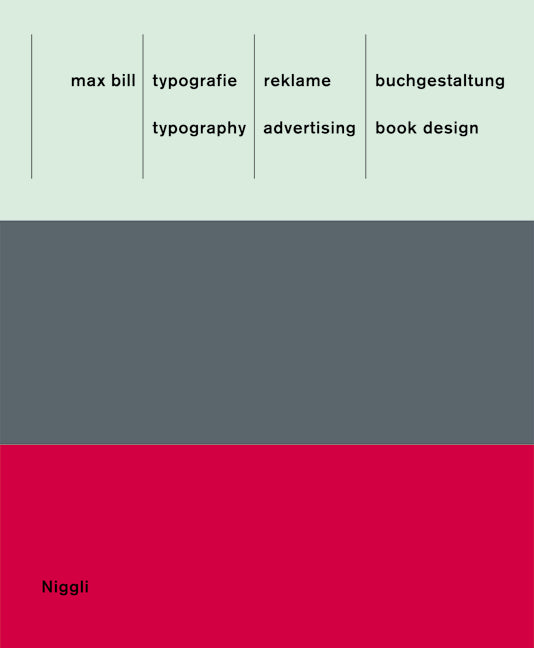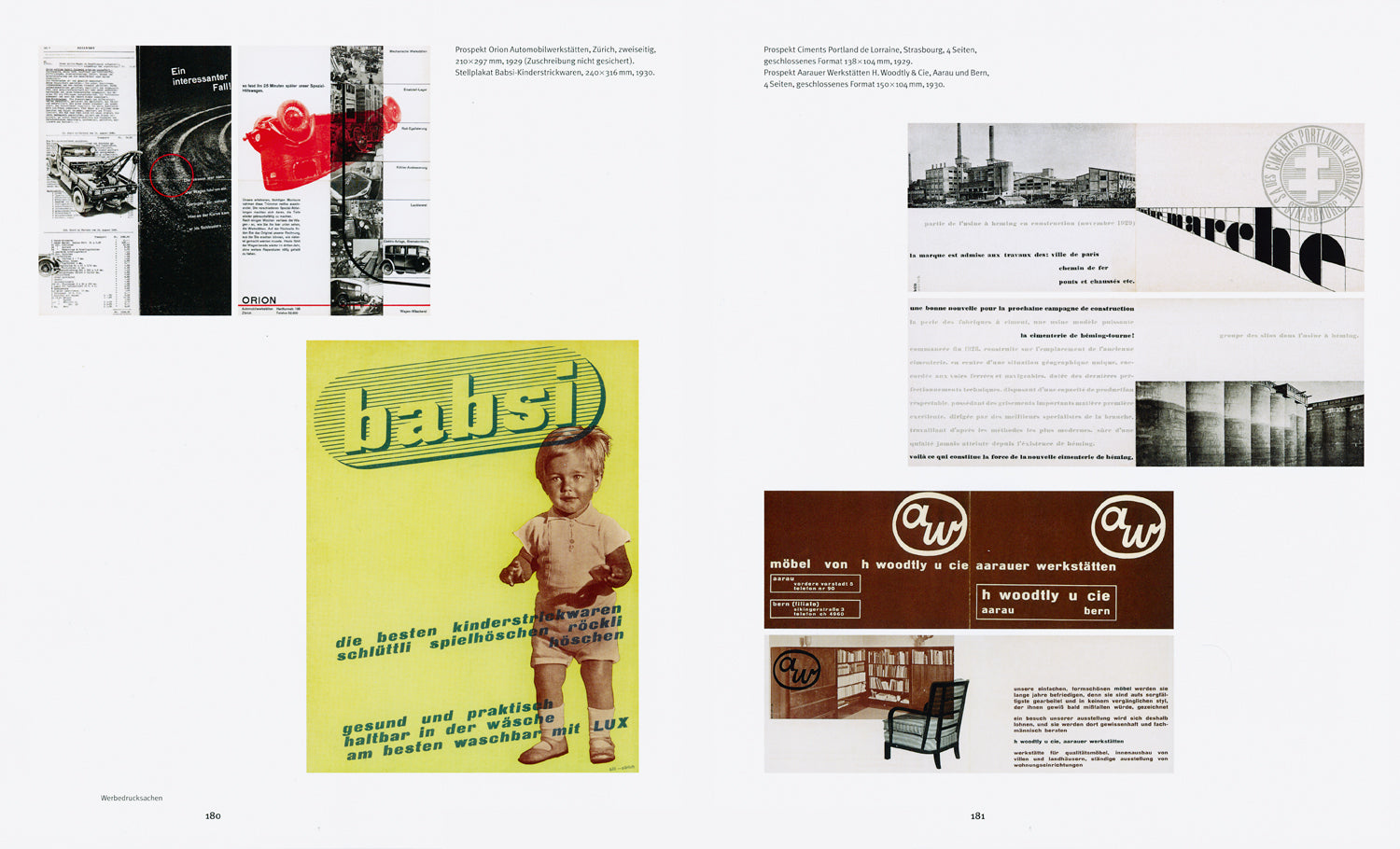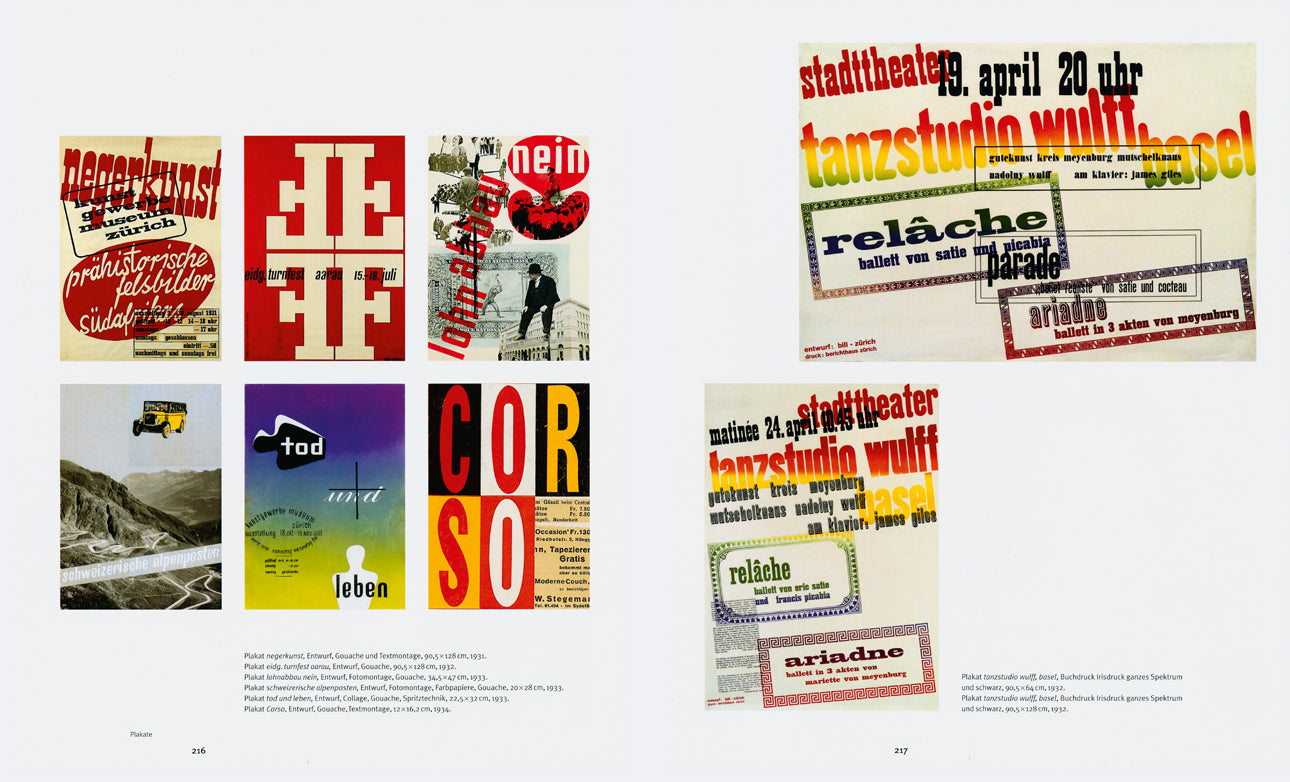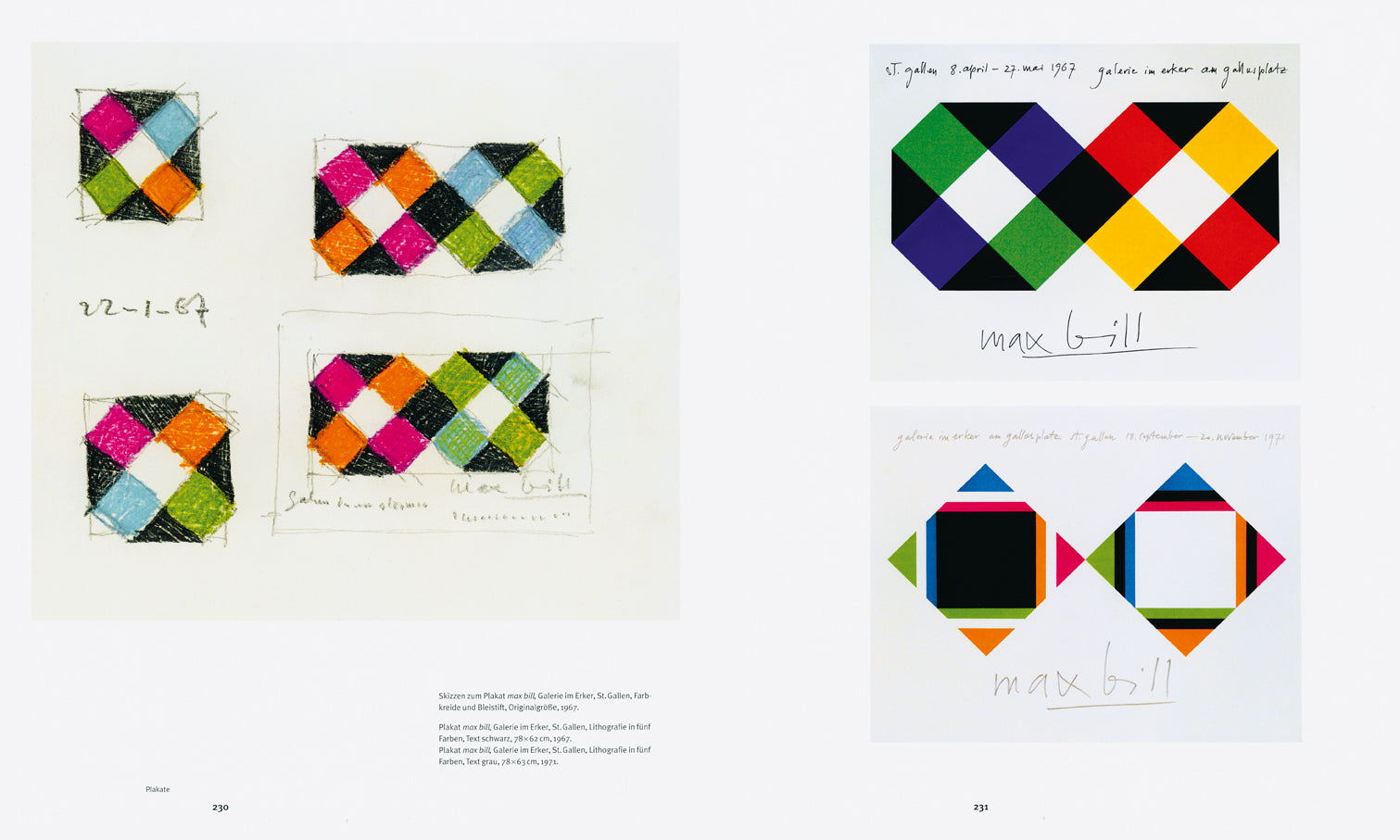
Max Bill: Typografie. Reklame. Buchgestaltung
Das vorliegende Buch gibt einen umfassenden Einblick in ein Gebiet aus dem Schaffen Max Bills, dem bisher wenig Aufmerksamkeit entgegengebracht wurde: seinen typografischen Arbeiten, Reklame- und Buchgestaltungen. Obwohl sich Max Bill zeitlebens am liebsten als Architekt sah, stammen gerade seine ersten Arbeiten mehrheitlich aus dem Gebiet der Gebrauchsgrafik und stellen einen wesentlichen Teil seines künstlerischen Œuvres dar. Die Publikation verdeutlicht, dass fast alles, was die schweizerische Avantgarde um 1930 an Lebens- und Wohnreform durchführte, im Atelier «bill-zürich reklame» für die Öffentlichkeit visualisiert wurde. Dieses im Vergleich mit anderen europäischen Zentren einzigartige Monopol eines Grafikers verleiht den hier erstmals umfänglich veröffentlichten gebrauchsgrafischen Arbeiten Bills einen hohen dokumentarischen Wert.
Zu entdecken ist Max Bill als unermüdlicher Entwerfer von eigenwilligen Schriften und Firmenlogos sowie auch als Gestalter, der über Bildwitz verfügt – ein nicht gerade häufiges Merkmal der konstruktiven Gestaltung hierzulande. Bill hat in seinen Schrifterfindungen zwei gegensätzliche Prinzipien verfolgt und damit zwei Linien in seinem Werk hinterlassen: eine zeichnerische und eine skulpturale. Ausgehend von der Universalschrift von Herbert Bayer hat er für die Siedlung Neubühl und die Firma «wohnbedarf» zwei Schriftzüge entwickelt, die von allen damals bekannten Formen abweichen. Der Grund für das breit gelagerte «o» mag in der Möglichkeit der seitlichen Betrachtung gelegen haben, dahinter stecken jedoch formale Ideen und das reduktionistische Konzept des Bauhauses.